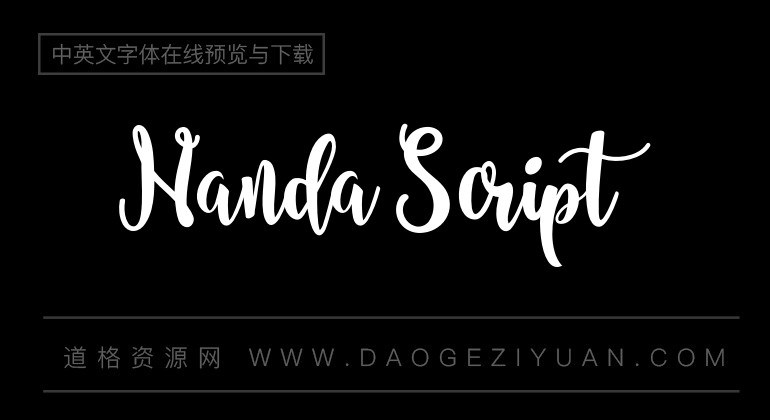
Nanda Script 是一种手写风格的字体,具有非常自然、流畅和美观的外观。该字体最初由 Insanitype 设计师 Fernando Haro 创建,并于 2014 年发布。 Nanda Script 字体呈现了一种装饰性弯曲的风格,字母之间的连通性非常强,使得整个字体看起来就像是手写的。该字体具有许多不同的字母形状和大小,包括一些与字母形状相关的额外连线,这些特征使得 Nanda Script 字体非常适合用于设计海报、包装、书籍封面等项目。 此外,Nanda Script 字体非常易于阅读,适合在各种大小的文本和标题中使用。该字体为 OpenType 字体,支持各种语言字符集,包括西里尔字母和中日韩文字。由于其自然、流畅和美观的特点,Nanda Script 字体成为了许多平面设计师和品牌设计师的首选字体之一。内容介绍
Nanda Script是一款非常不错的手写艺术字体,具有很好的视觉感,适合于文化类的宣传设计、商业类品牌的广告和产品包装设计以及个性化文字排版等较多场景。